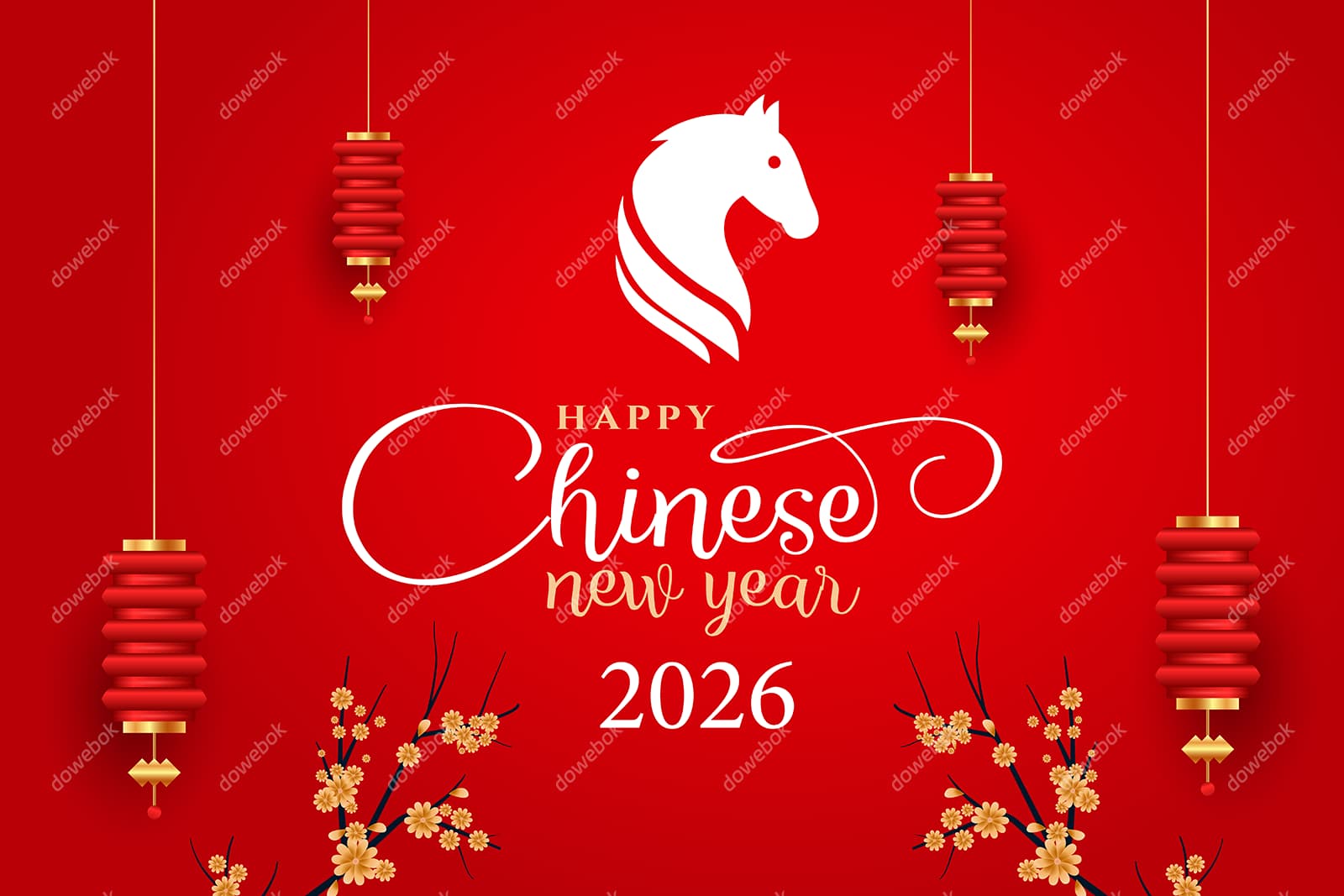
这是一款灯笼和梅花设计 2026 春节快乐矢量素材,暖红渐变背景晕染出热烈氛围,正红背景铺展节日喜庆,两侧悬垂的红灯笼、底部绽放的金梅,都是中式年俗元素。中央白描马首契合马年生肖,搭配花体 “Happy Chinese New Year” 与 “2026” 字样,以红金主色调融合传统符号与现代字体,既显春节的红火氛围,又透出雅致的生肖主题质感。